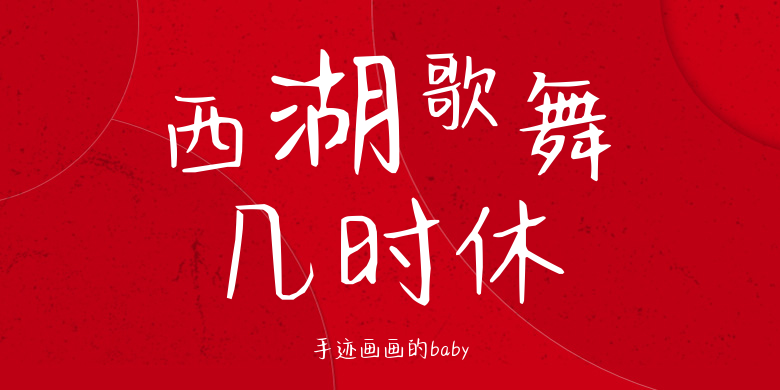
手迹画画的baby
手迹画画的baby,这款字体结构工整、笔画清晰,兼顾美观与易读性,适用于标题、正文、海报、包装、LOGO 等多种场景。字形优雅稳定,风格百搭耐看,适配日常排版与创意设计,让文字呈现更舒适、更具质感。手迹画画的baby一笔一画,皆是细节,以均衡的比例、流畅的线条打造舒适视觉体验,字形端正大气,风格简约现代。无论是商业设计、品牌宣传还是日常排版,都能轻松驾驭,让文字更有格调与力量。手迹画画的baby字体下载。